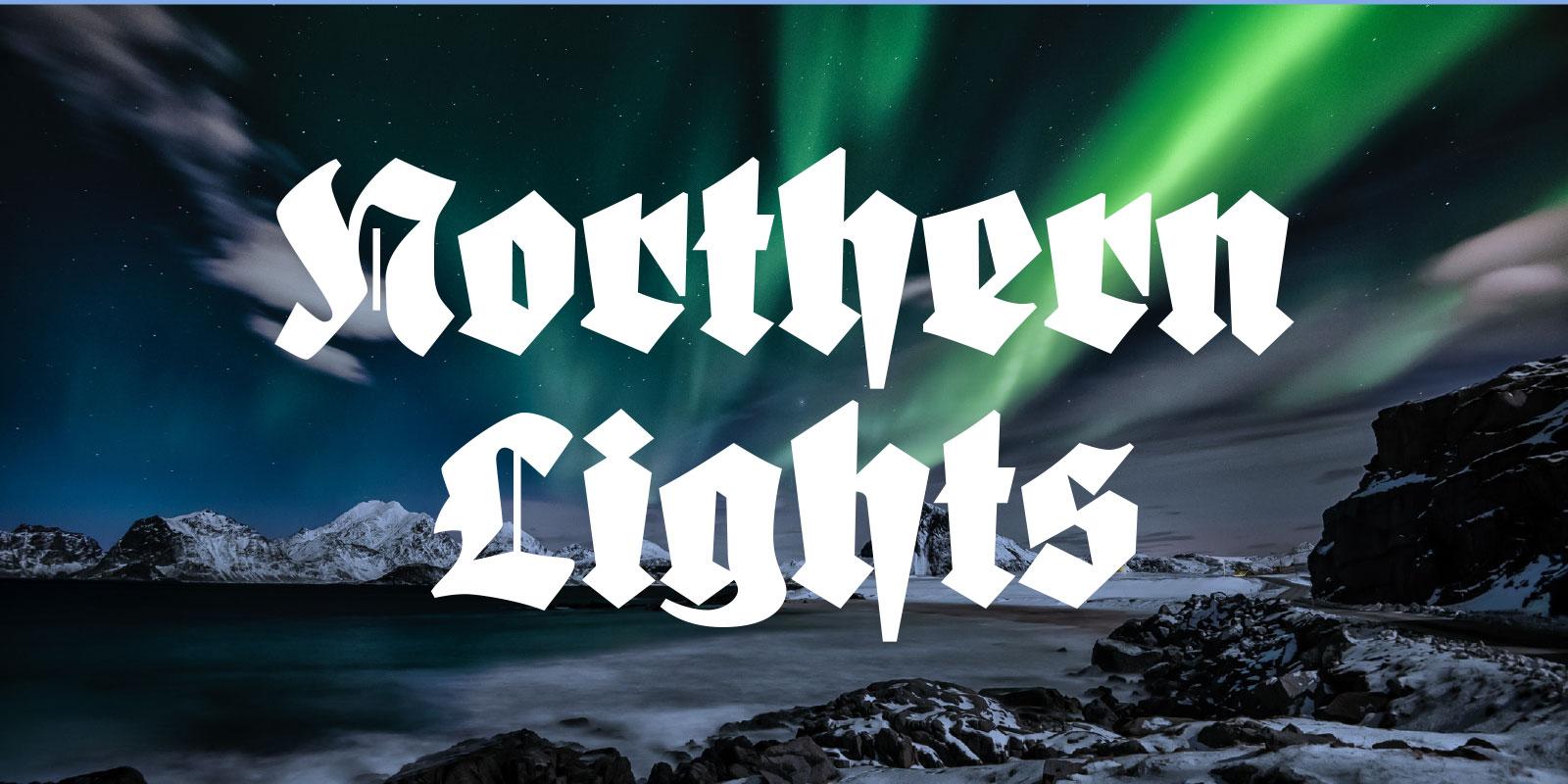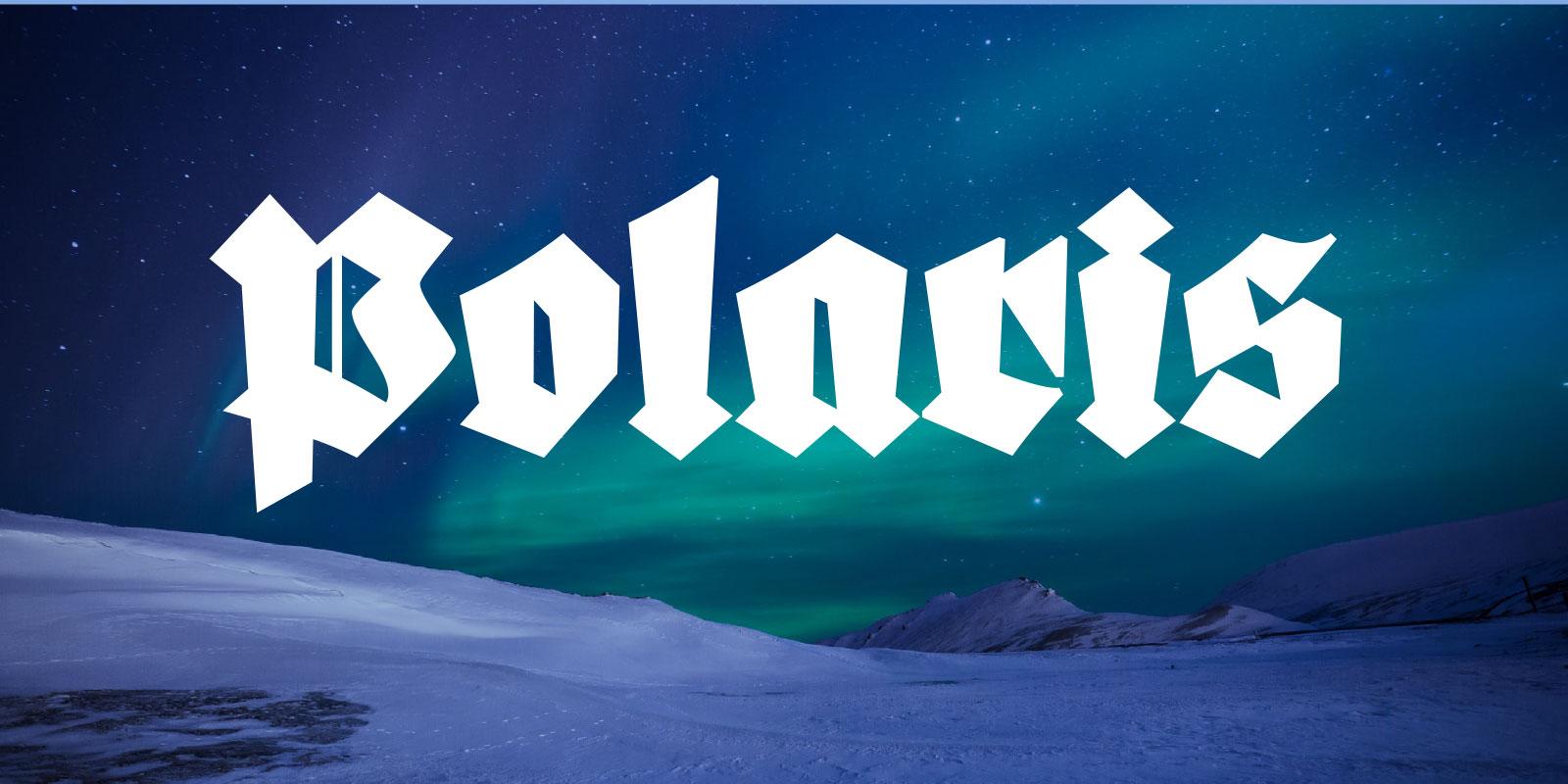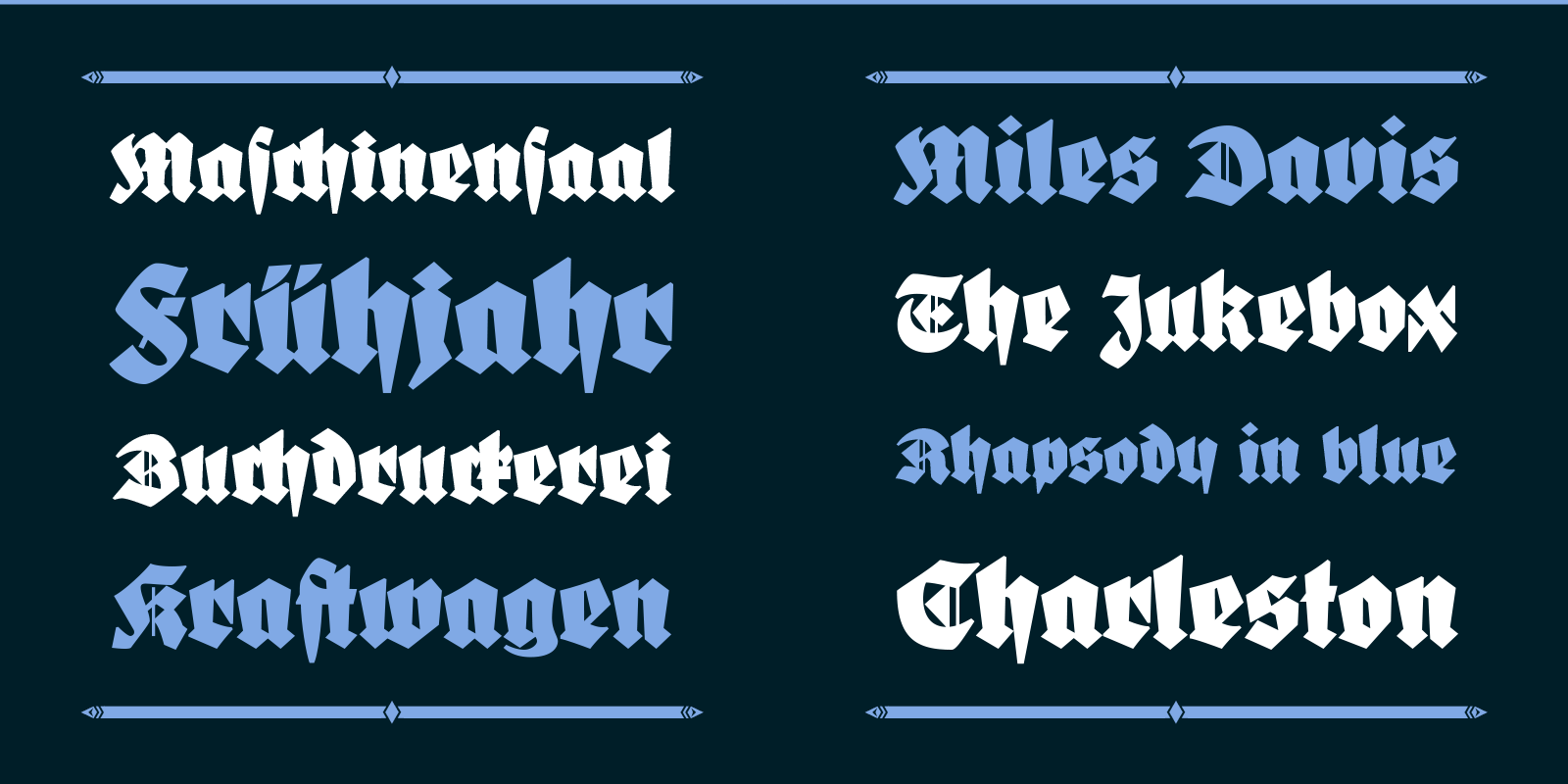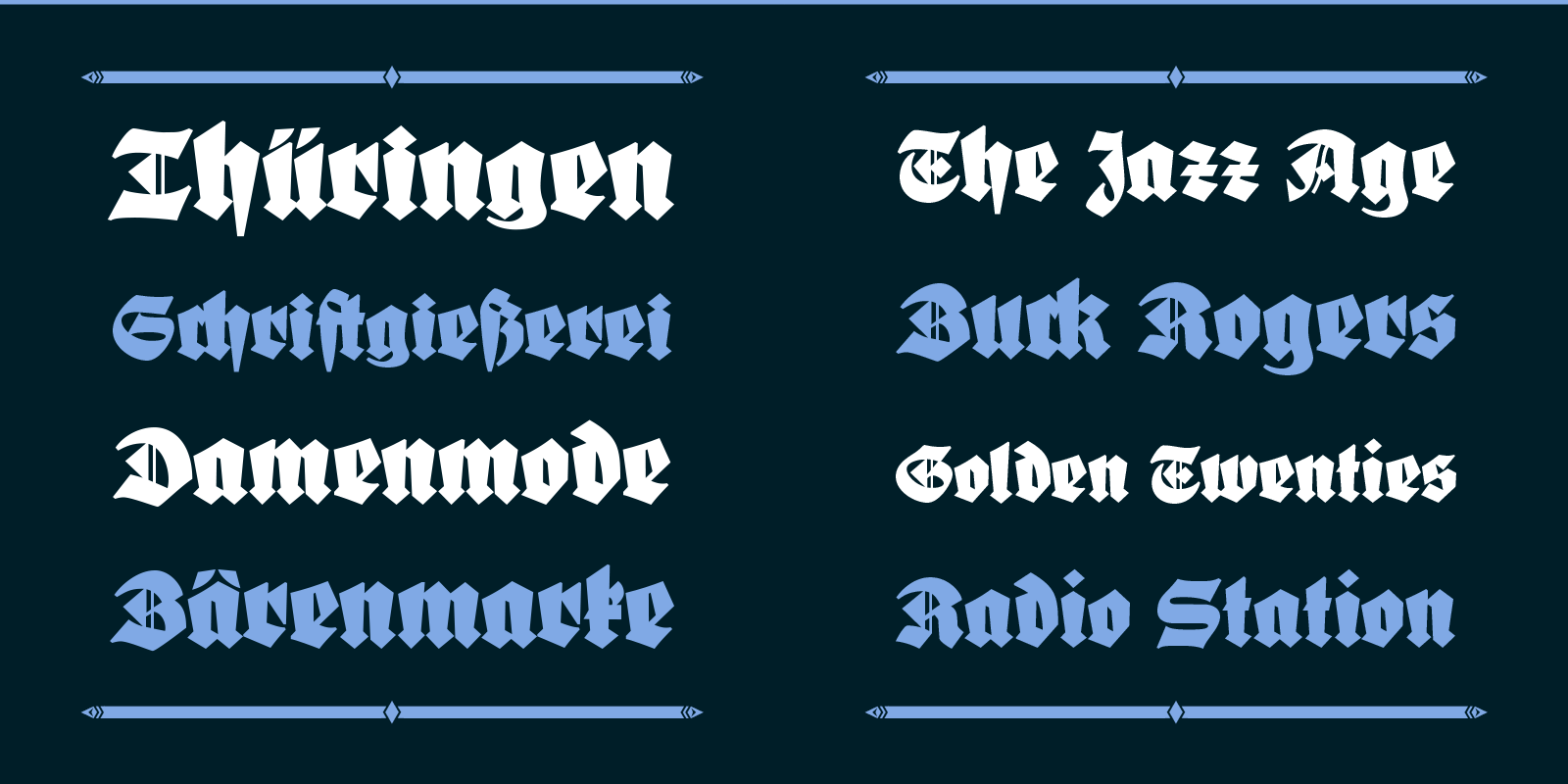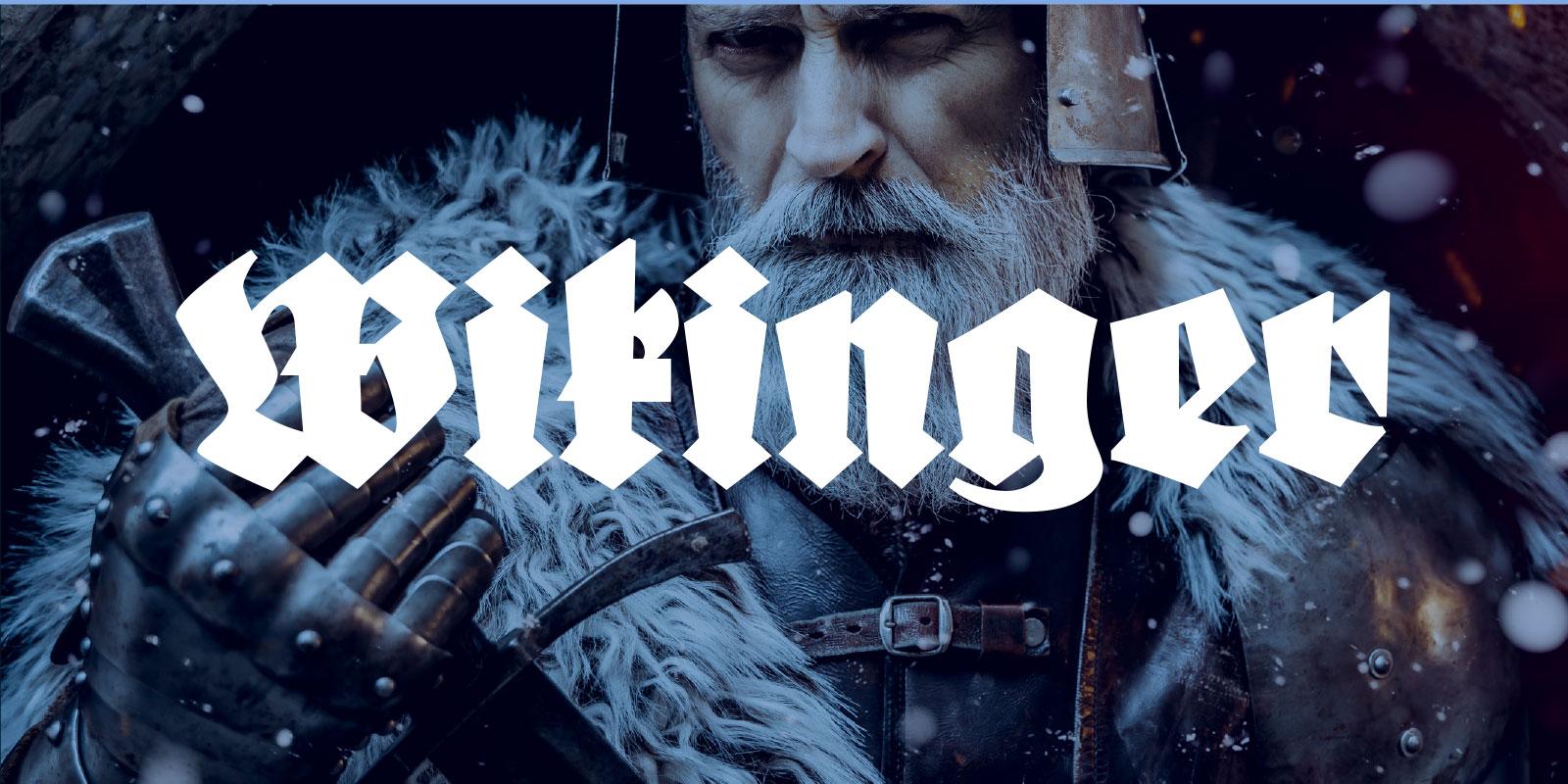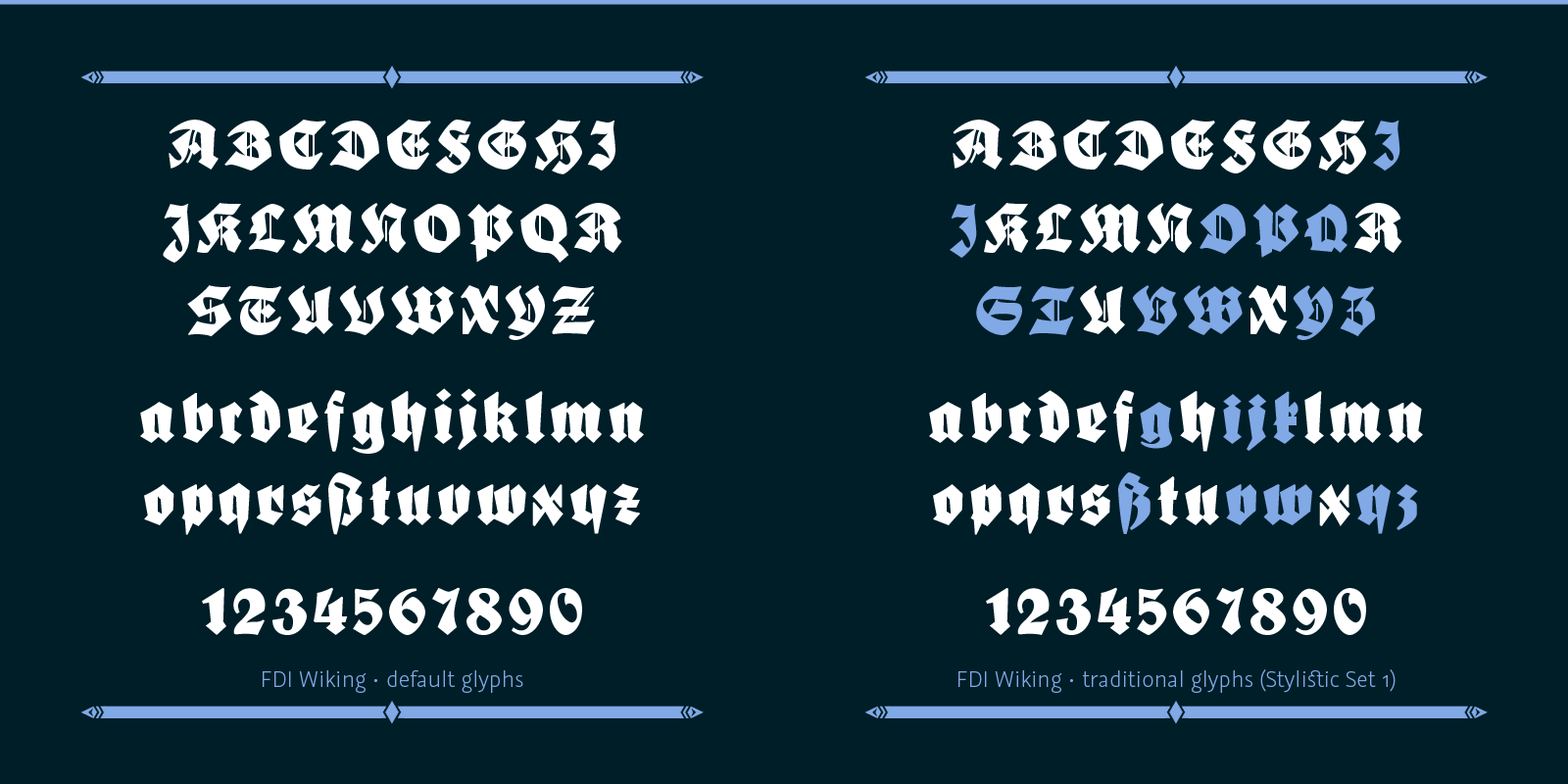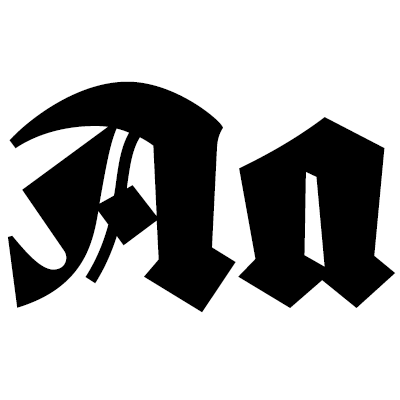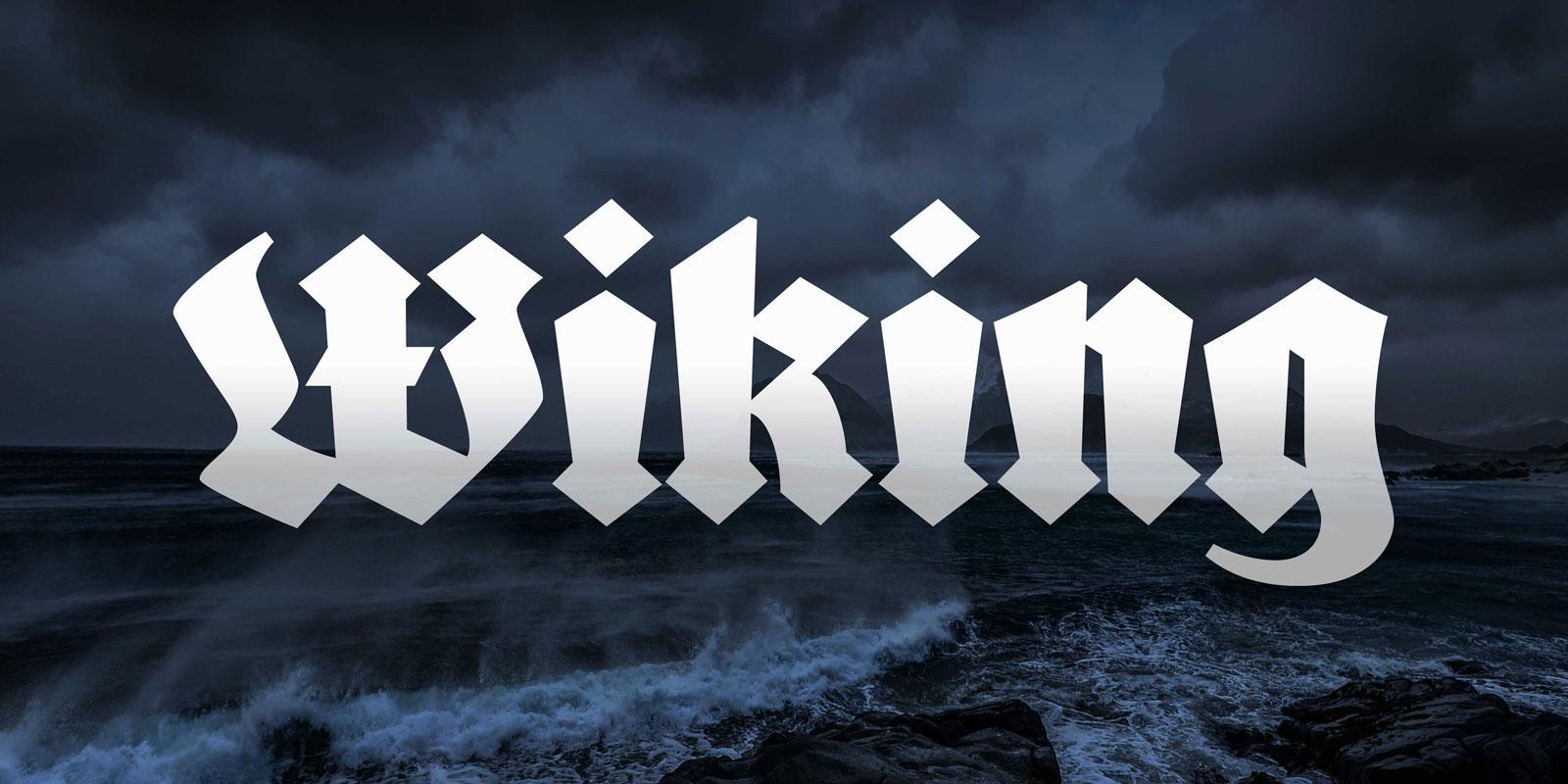
Eine sorgfältige und vollständige, über Kickstarter finanzierte Digitalisierung der Wiking-Schrift der Gießerei J.D. Trennert & Sohn (1925).
Traditioneller Fraktursatz mit allen Ligaturen und als Varianten hinterlegten historischen Zeichenformen ist über die OpenType-Funktionen »bedingte Ligaturen« und »Stilsatz 1« möglich.